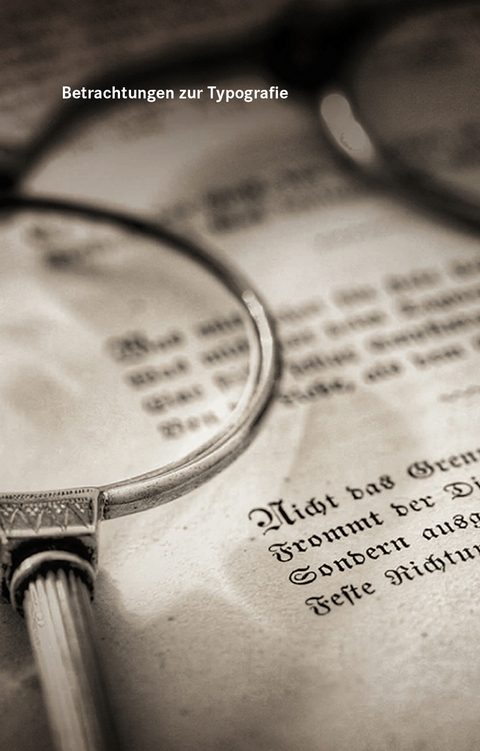
Betrachtungen zur Typografie
"Betrachtungen zur Typografie" - ein Typobüchlein zum Einsetzen der richtigen TypografieDiese "Betrachtungen zur Typografie" entstammen einer Artikelreihe für die Macintosh-Fachzeitschrift "Macwelt". Das Buch hilft im Alltag in den wichtigsten typografischen Situationen mit Hilfestellungen und Hinweisen. Die wichtigsten typografischen Regeln werden ausführlich erklärt und auch optisch an einzelnen Beispielen erklärt. Je mehr Sie darauf achten, desto wichtiger und damit einfacher wird für Sie die korrekte Typografie. Es bleibt nicht aus, auch in ebenfalls optischen Beispielen auf fehlerhafte Anwendung von Typografie hinzuweisen. Aber je mehr sie sich an den positiven Beispielen orientieren, die das Buch aufzeigt, umso weniger kann Ihnen zukünftig ein Fehler unterlaufen.
Thomas Biedermann, geb. 1961, hat ein sozialwissenschaftliches Studium in Politologie, Soziologie und VWL an den Universitäten Heidelberg und Hamburg absolviert. Er ist geprägt durch ein humanistische Bildungsideal und eine Studienzeit vor der verschulten Bachelor-/Master-Ära, in der er oft in fremden Fachbereichen in Vorlesungen/Seminaren 'über den Tellerrand' geschaut hat. Thomas Biedermann hat jedoch seine studienbegleitende Tätigkeit als Grafik-Designer ausgeweitet, seinen Berufsabschluss als Mediengestalter nachgeholt und ist seit vielen Jahren als selbständiger Grafik-Designer tätig.
In der Typografie gibt viele Regeln, die es zu beachten gilt, will man ein harmonisches Schriftbild erreichen. (...) Doch dafür muss man die typografischen Regeln erst einmal kennen. Thomas Biedermann hat eine dreiteilige Artikelserie zur Typografie für die Zeitschrift "Macwelt" geschrieben, die auch in seinem Buch "Betrachtungen zur Typografie" zusammengefasst ist. In dem Buch werden die Todsünden der typografischen Gestaltung aufgezählt und erläutert, wie man es richtig macht. Das kleine Werk, welches auf knapp 70 Seiten die Regeln der Typografie zusammenfasst, ist optimal als ständiger Begleiter geeignet, wenn man typografische Sünden vermeiden will. Die Regeln werden so anschaulich beschrieben, dass dieses Buch auch für Anfänger geeignet ist, die sich im Setzen von Texten für Print- und Webmedien versuchen wollen bzw. aus Berufs-/Studiumszwecken müssen. Natürlich sind in diesem kleinen Werk nicht alle Regeln aufgelistet, es bietet jedoch eine anschauliche Übersicht über die gröbsten Verstöße. Thomas Biedermann gibt Hilfestellungen zu alltäglichen Situationen mit vielen Tipps und Regelhinweisen. Dieses Buch ist nicht nur für Gestalter und Texter geeignet, sondern auch für Menschen, die ansprechende Bewerbungsschreiben und andere Anschreiben gestalten wollen. Sicherlich wird aber auch der eine oder andere Texter hier Hinweise und Regeln finden, die ihm "neu" sind. - Robert Krippgans, grafiker.de, 27.01.2010
In der Typografie gibt viele Regeln, die es zu beachten gilt, will man ein harmonisches Schriftbild erreichen. (…) Doch dafür muss man die typografischen Regeln erst einmal kennen. Thomas Biedermann hat eine dreiteilige Artikelserie zur Typografie für die Zeitschrift „Macwelt“ geschrieben, die auch in seinem Buch „Betrachtungen zur Typografie“ zusammengefasst ist. In dem Buch werden die Todsünden der typografischen Gestaltung aufgezählt und erläutert, wie man es richtig macht. Das kleine Werk, welches auf knapp 70 Seiten die Regeln der Typografie zusammenfasst, ist optimal als ständiger Begleiter geeignet, wenn man typografische Sünden vermeiden will. Die Regeln werden so anschaulich beschrieben, dass dieses Buch auch für Anfänger geeignet ist, die sich im Setzen von Texten für Print- und Webmedien versuchen wollen bzw. aus Berufs-/Studiumszwecken müssen. Natürlich sind in diesem kleinen Werk nicht alle Regeln aufgelistet, es bietet jedoch eine anschauliche Übersicht über die gröbsten Verstöße. Thomas Biedermann gibt Hilfestellungen zu alltäglichen Situationen mit vielen Tipps und Regelhinweisen. Dieses Buch ist nicht nur für Gestalter und Texter geeignet, sondern auch für Menschen, die ansprechende Bewerbungsschreiben und andere Anschreiben gestalten wollen. Sicherlich wird aber auch der eine oder andere Texter hier Hinweise und Regeln finden, die ihm „neu“ sind. - Robert Krippgans, grafiker.de, 27.01.2010
Vorwort
"Was sind die Todsünden der Typografie? Falsch verwendete Schriftzeichen anstelle typografischer Sonderzeichen zum Beispiel. Die FAZ macht s falsch, prominente Firmen verwenden es auf ihrer Website und sogar in der Fernsehwerbung falsch, und wenn ich die Printmedienlandschaft durchforste, sträuben sich mir manchmal die Nackenhaare.
Sträflich auch die falsche Anwendung durch manchen Grafiker-Kollegen. Einige ziehen nur die Schultern hoch und sagen:"Ach, das ist nicht sooo wichtig! Das geht schon!"Leider lädt auch das Internet nicht zur korrekten Verwendung typografischer Regeln ein, denn viele Typozeichen sind bei der Gestaltung einer Site nur mühsam manuell durch einen Code in den Text einzugeben. Oder manche Browser interpretieren die Kodierung der Website für das typografisch Korrekte nicht richtig.
Unverständlich und fast schon strafbar aber, dass noch kein Designer unsere High-Tech-Computertastaturen überarbeitet und die korrekten An- und Abführungszeichen, Gedanken striche und Auslassungszeichen an gut erreichbarer Stelle eingefügt hat und zumindest die Zollzeichen in den Papierkorb verbannt. Das ist einer Hinführung des Normal-Anwenders zu einer korrekten Verwendung typografischer Zeichen nicht zuträglich. Eigentlich gehören die alten Tastaturen verboten!
Ich bin in Printmedien schondes Öfteren über typografische Fehler - z. B. Bindestriche anstelle von Gedankenstrichen - gestolpert, bei denen ich den gleichen Satz eine Minute lang mehrmals lesen musste, bis ich verstand, was der Autor eigentlich sagen will. Wer auf solche Schriftvergewaltigungen stößt, ist froh, abends in einer Zeitschrift zu blättern, die typografisch korrekt gesetzt wurde. Das erleichert das Lesen, das Verständnis und - tut der Seele gut.
Dies ist kein Büchlein, in dem mit erhobenemZeigefinger gearbeitet wird. Aber es weist deutlich auf zwei Dinge hin: die"Do's"und die"Dont's". Sie erkennen sofort die Fallstricke, über die Sie stolpern können, und wie Sie sie elegant und typografisch richtig umgehen. Wenn Sie sich an den Beispielen orientieren, kann Ihnen kein Fehler mehr unterlaufen. Je mehr Sie da-rauf achten, desto wichtiger und damit einfacher wird für Sie die korrekte Typografie.
Wenn Sie als Setzer - sei es als Amateur oder Profi - Print- oder auch Webmedien setzen und diese Ratschläge beherzigen, dankt es Ihnen der wichtigste Part der Medienkette: Ihr Leser. Er wird sich darüber freuen, wenn das Lesen augen- und lesefreundlich vonstatten geht und angenehm ist...."